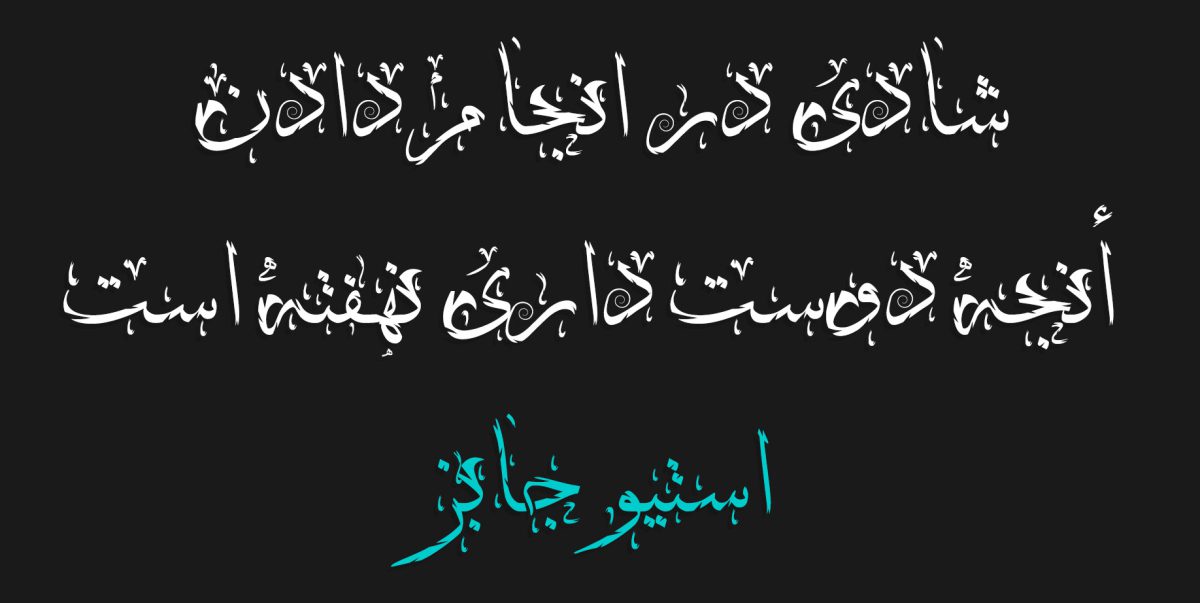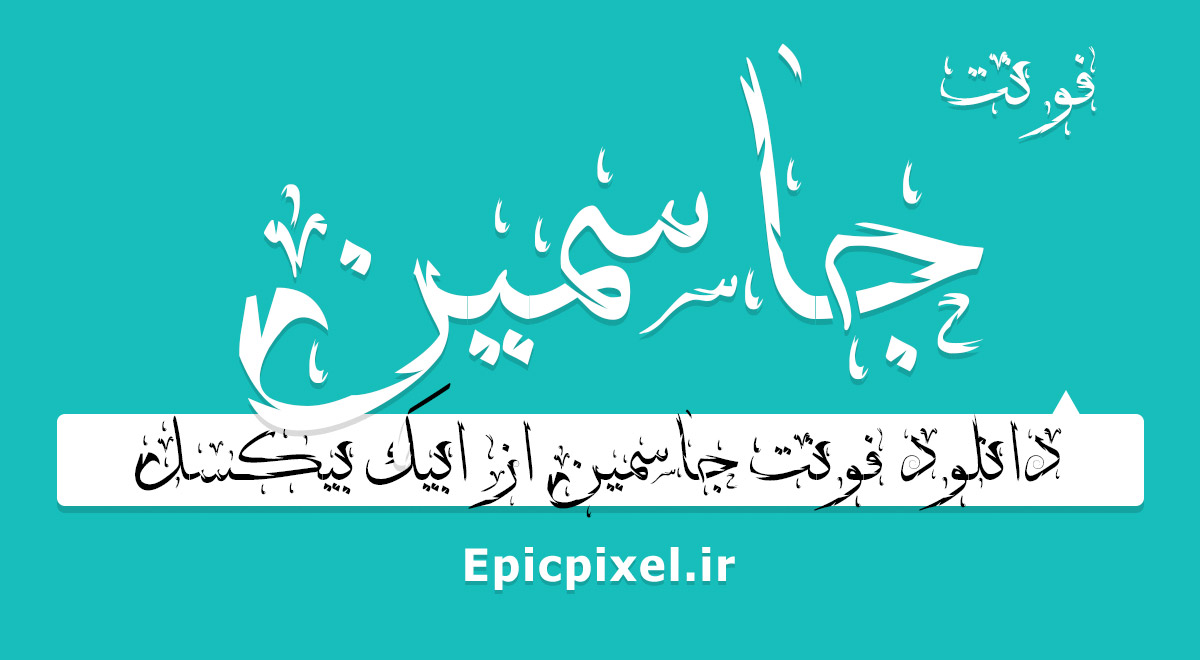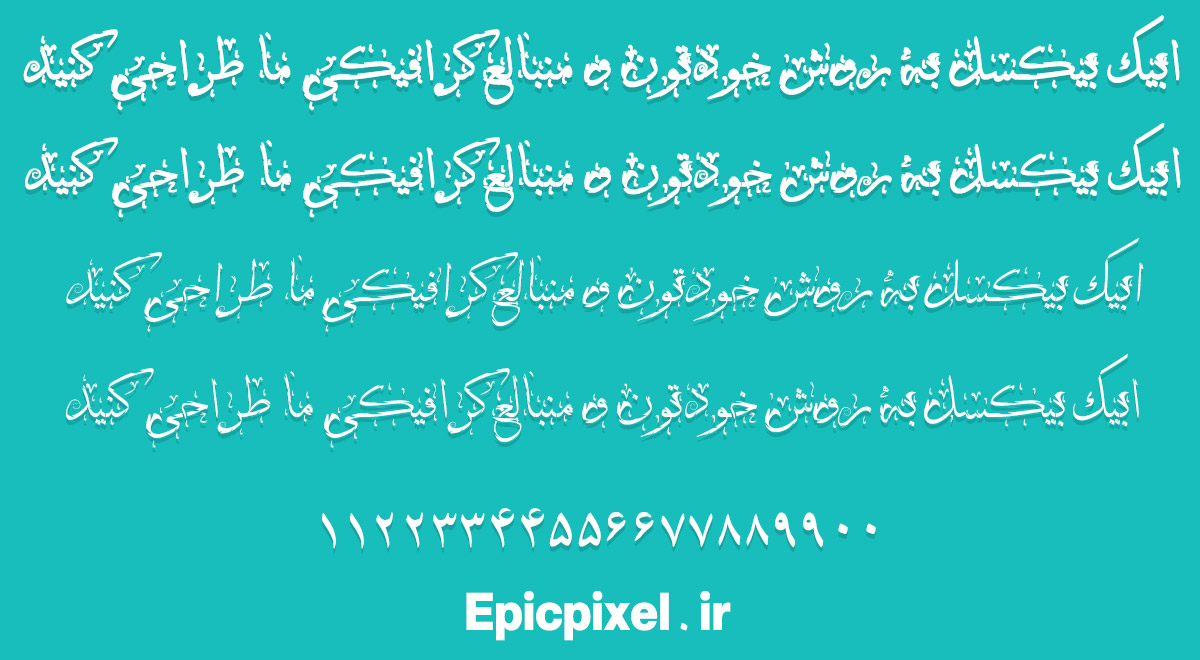
فونت جاسمین فارسی Jassmin
دانلود رایگان فونت جاسمین فارسی (Jassmin)، یک قلم تک وزن با طراحی خوشنویسی و تزئینی است که در دو فرمت OTF و TTF ارائه شده است. این فونت، نسخه ای اصلاح شده از یک قلم عربی است که با ویژگی های خاص خود، جلوه ای منحصر به فرد به متون فارسی می بخشد. جاسمین فاقد برخی حروف فارسی مانند “پ” (که با “ب” جایگزین شده) و حروف انگلیسی و برخی علائم است. برجسته ترین ویژگی آن، وجود علائم تزئینی در بین حروف برای زیبایی بیشتر و افکت بریدگی تیر در داخل حروف است. این فونت با سبک نستعلیق و نسخ و نوشتاری کشیده، برای کاربردهای هنری، تزئینی و گرافیک سنتی ایده آل است.
فونت جاسمین رایگان فارسی Jassmin: قلم خوشنویسی تزئینی با حال و هوای سنتی
فونت جاسمین فارسی (Jassmin) یک قلم منحصر به فرد و با سبک خاص است که برای خلق آثاری با حس و حال خوشنویسی سنتی طراحی شده است. این فونت تک وزن است و در دو فرمت رایج OTF (OpenType Font) و TTF (TrueType Font) در دسترس قرار می گیرد که سازگاری گسترده ای با نرم افزارهای مختلف را تضمین می کند.
طراحی و ویژگی های بصری: فونت جاسمین در اصل یک فونت خوشنویسی عربی بوده که برای استفاده در زبان فارسی اصلاح شده است. با این حال، به دلیل این اصلاحات، دارای برخی محدودیت ها و ویژگی های بصری خاص است:
- کشیدگی و پیچش: نوشتار این فونت دارای کشیدگی ها و پیچش های زیباست که یادآور سبک های نستعلیق و نسخ است. این ویژگی به متن جلوه ای روان و هنری می بخشد.
- تزئینات داخلی و خارجی: یکی از جذاب ترین جنبه های فونت جاسمین، وجود علائم تزئینی در بین حروف است که به زیبایی بصری متن می افزاید. علاوه بر این، افکت “بریدگی تیر” در داخل برخی حروف، به آن حالتی خاص و چشمگیر می دهد که آن را از سایر فونت ها متمایز می کند.
- محدودیت حروف: نکته مهمی که باید به آن توجه داشت این است که این فونت فاقد برخی حروف فارسی مانند “پ” است که در صورت تایپ، با حرف “ب” جایگزین می شود. همچنین، این فونت فاقد حروف انگلیسی و برخی از علائم استاندارد است. این ویژگی ها آن را بیشتر برای کاربردهای تزئینی و عنوانی مناسب می سازد تا متون طولانی و عمومی.
این فونت برای ایجاد حس و حال قدیمی، سنتی و خوشنویسی در طراحی های شما بسیار کاربردی است.
کاربردهای فونت جاسمین در طراحی های هنری و سنتی
فونت جاسمین فارسی (Jassmin) با ظاهر خوشنویسی، کشیدگی ها و تزئینات خاص خود، برای طیف وسیعی از کاربردها در حوزه های هنری، فرهنگی، مذهبی و تزئینی بسیار مناسب است. این فونت برای ایجاد حس اصالت و زیبایی در طرح های شما ابزاری منحصربه فرد است.
این فونت برای طراحی عناوین اصلی و تیترها در پوسترها، بنرها و تابلوهای هنری یا مذهبی که نیاز به جلوه ای خاص و چشمگیر دارند، بسیار مناسب است. در طراحی جلد کتاب ها، مجلات و نشریاتی با مضامین ادبی، تاریخی، عرفانی یا مذهبی، می تواند حس اصالت و قدمت را القا کند.
فونت جاسمین برای کارت های تبریک و دعوت نامه های سنتی یا مذهبی، و همچنین برای بسته بندی محصولات فرهنگی و صنایع دستی که به دنبال بازتاب هویت ایرانی-اسلامی هستند، گزینه ای عالی است. طراحان لوگو و هویت بصری برای کسب وکارهایی با رویکرد سنتی، گالری های هنری یا مجموعه های فرهنگی می توانند از این فونت بهره ببرند. همچنین، در طراحی های گرافیکی با مضمون خوشنویسی و دیجیتال آرت که هدف خلق اثری هنری با تمرکز بر زیبایی خط فارسی است، جاسمین به خوبی ایفای نقش می کند. به دلیل ویژگی های خاص حروف و علائم داخلی آن، بیشتر برای متون کوتاه و نمایشی توصیه می شود تا متون بلند.